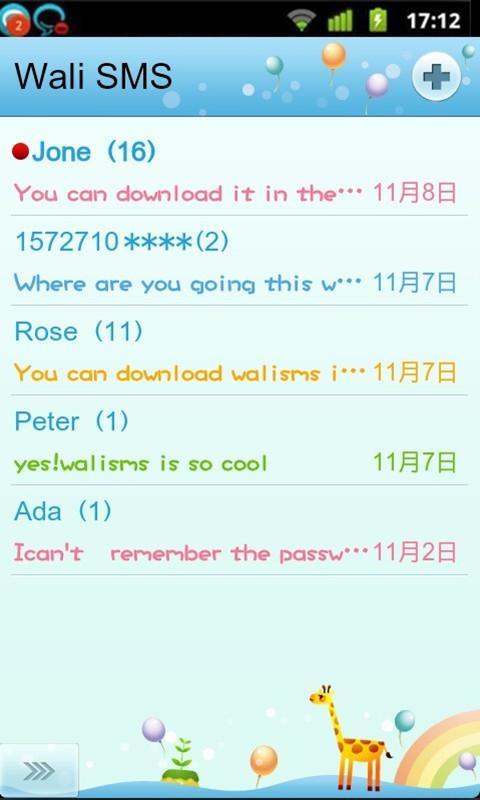
WALI SMS DOLL FONT هو تطبيق خط لطيف.
Wali SMS Doll Font plug-in هو تطبيق مكون من ذلك يطبق على Walisms. مع مثل هذا الخط اللطيف ، من المؤكد أنك ستقع في حب الرسائل النصية.